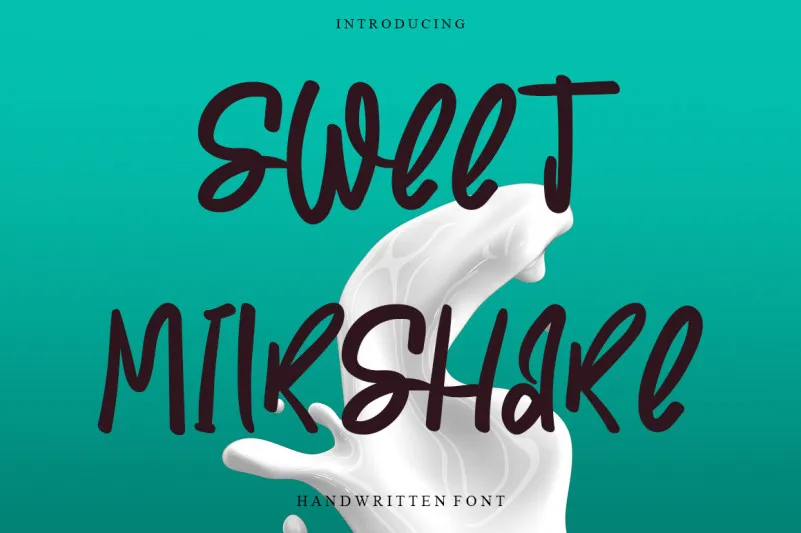
Sweet Milkshake Font – Download Grátis
A Sweet Milkshake Font é uma elegante mistura de letras escritas a mão, perfeita para aqueles que buscam algo um pouco diferente no design do seu projeto. Seu estilo casual e irreverente torna-a ideal para aplicações como cartões de boas-vindas, papel de scrapbooking e até mesmo em logotipos criativos, trazendo personalidade sem perder elegância. Sua natureza suave e acessível faz dela uma opção perfeita para qualquer projeto que exija um toque pessoal e descontraído no design. Envolventemente agradável à vista e extremamente funcional, esta fonte é certamente o tipo de grana do qual todo designer precisa em seu arsenal.